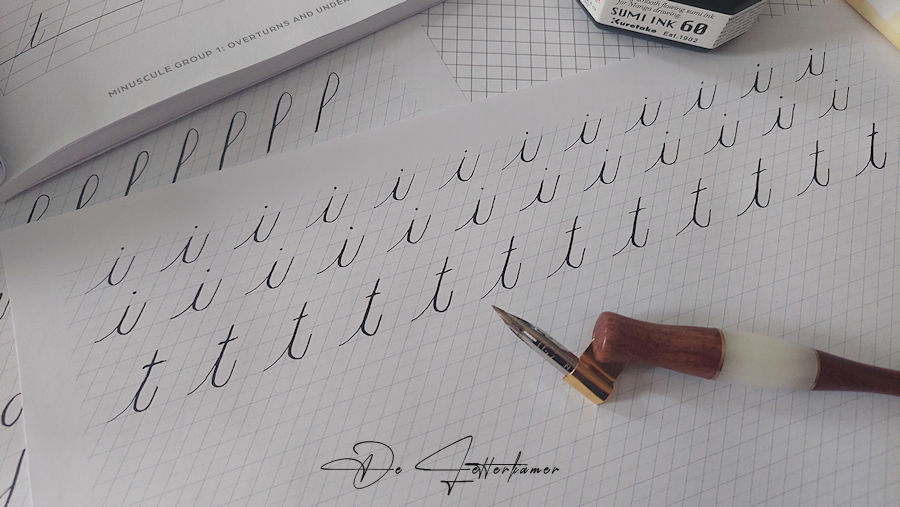
Ik had net daarvoor mijn oefening al gemaakt, ik wist dat het er niet meer ging van komen anders. Ik had me voorgenomen om nu eens met de volgende groep te beginnen. Groep 1: de letters met de overturns & underturns.
Dit boek volg ik nu.
In die groep zitten de letters “i” en “t”, maar eerst heb ik weer mijn hand opgewarmd, een paar krullen gemaakt en nog enkele basisvormen.
Hier heb ik er enkele geschreven van die 1ste groep, ik kon me niet meer houden.
Ik moet zeggen het gaat redelijk goed. Ik neem mijn tijd en zeker niet langer dan een uur. Al wat méér is, is teveel, en het lukt niet meer zo goed, de focus verdwijnt. Wat me wel opvalt dat bij de letter “t” de pen vlugger blijft haperen aan mijn papier, de lijnen zijn niet altijd even goed, ik gebruik nog steeds printpapier Clairefontainte DCP 90g.